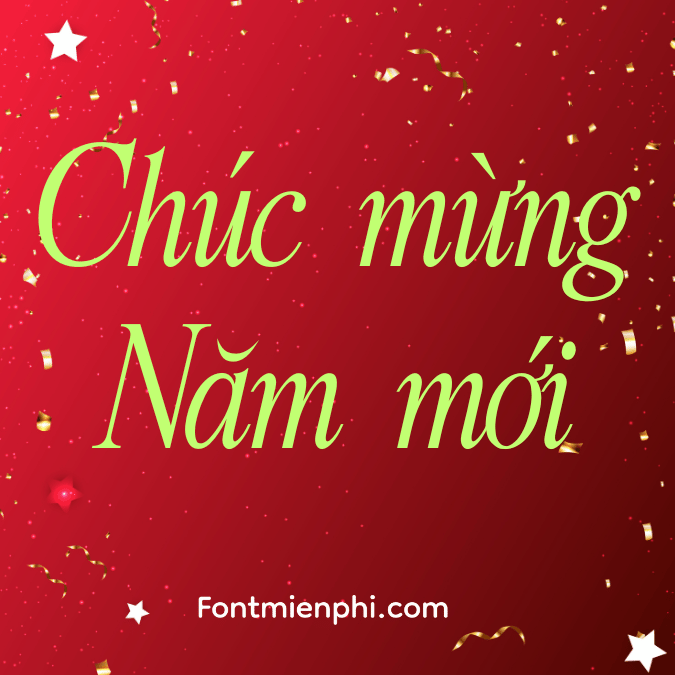
FONT VIỆT HÓA 1FTV VIP RELATIONSHIP OF MÉLODRAME
“Dòng chữ của những câu chuyện đầy cảm xúc”
ĐẶC ĐIỂM NỔI BẬT
✨ Phong cách lãng mạn – kịch tính: Lấy cảm hứng từ typography phim điện ảnh Pháp, kết hợp nét thanh mảnh quyến rũ với những điểm nhấn bất ngờ
Chất Mélodrame đích thực: Độ tương phản nét mạnh – yếu tạo hiệu ứng “kịch tính” trong từng con chữ
Tối ưu tiếng Việt: Full bộ dấu chuẩn, hỗ trợ đa nền tảng từ in ấn đến digital
ỨNG DỤNG VÀNG
• Thiết kế poster phim, album nhạc Indie
• Bao bì mỹ phẩm cao cấp, nước hoa
• Thiệp mời sang trọng, tạp chí nghệ thuật
• Nhận diện thương hiệu boutique, quán café nghệ sĩ
BỘ VIP ĐẶC BIỆT
5 phiên bản độc quyền:
- Regular (nền trắng)
- Shadow (đổ bóng kịch tính)
- Ornamental (hoa văn Baroque)
- Rough (hiệu ứng cọ vẽ)
- Extrabold (dành cho headline)
“Mỗi con chữ là một phân cảnh đầy cảm xúc…”
GỢI Ý THIẾT KẾ
• Màu chủ đạo: Đỏ rượu vang #9A031E + Kem #F7F0F0
• Kết hợp hình ảnh: Ảnh film grain, texture giấy cũ
• Hiệu ứng: Glitch nhẹ cho phiên bản digital